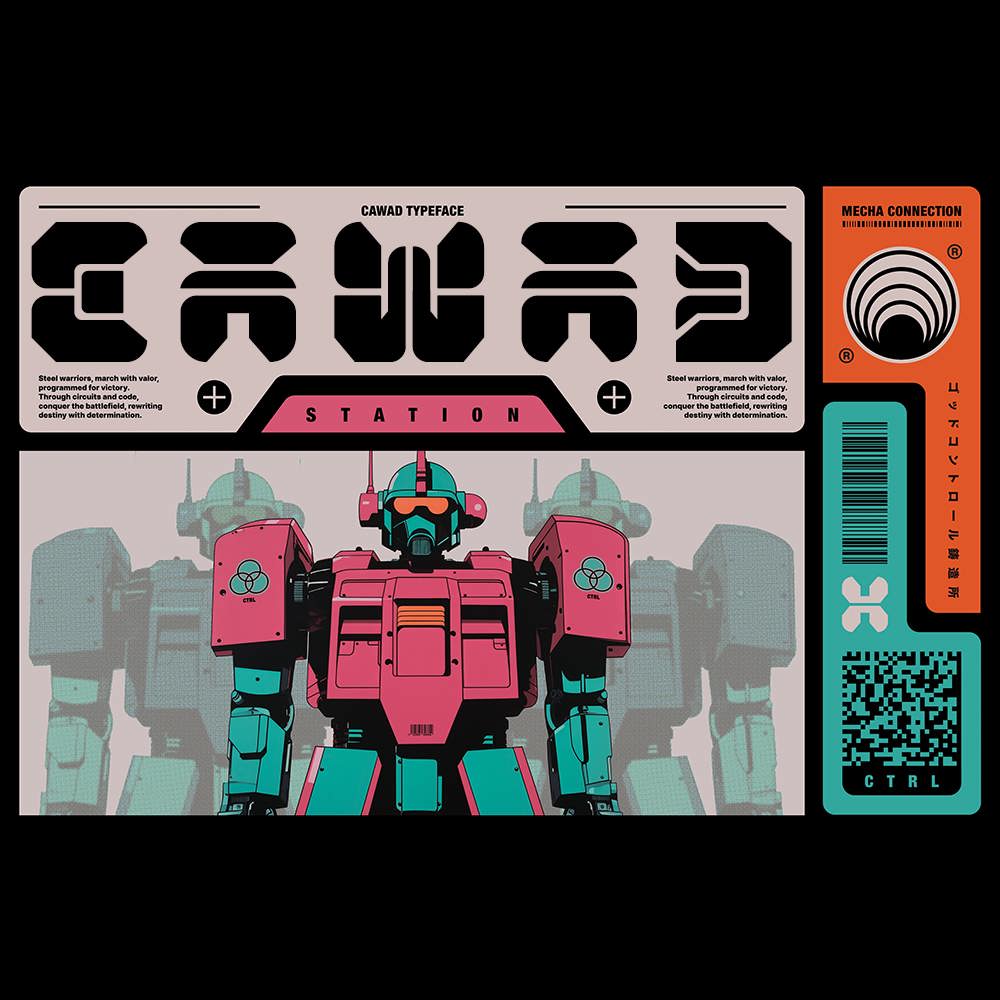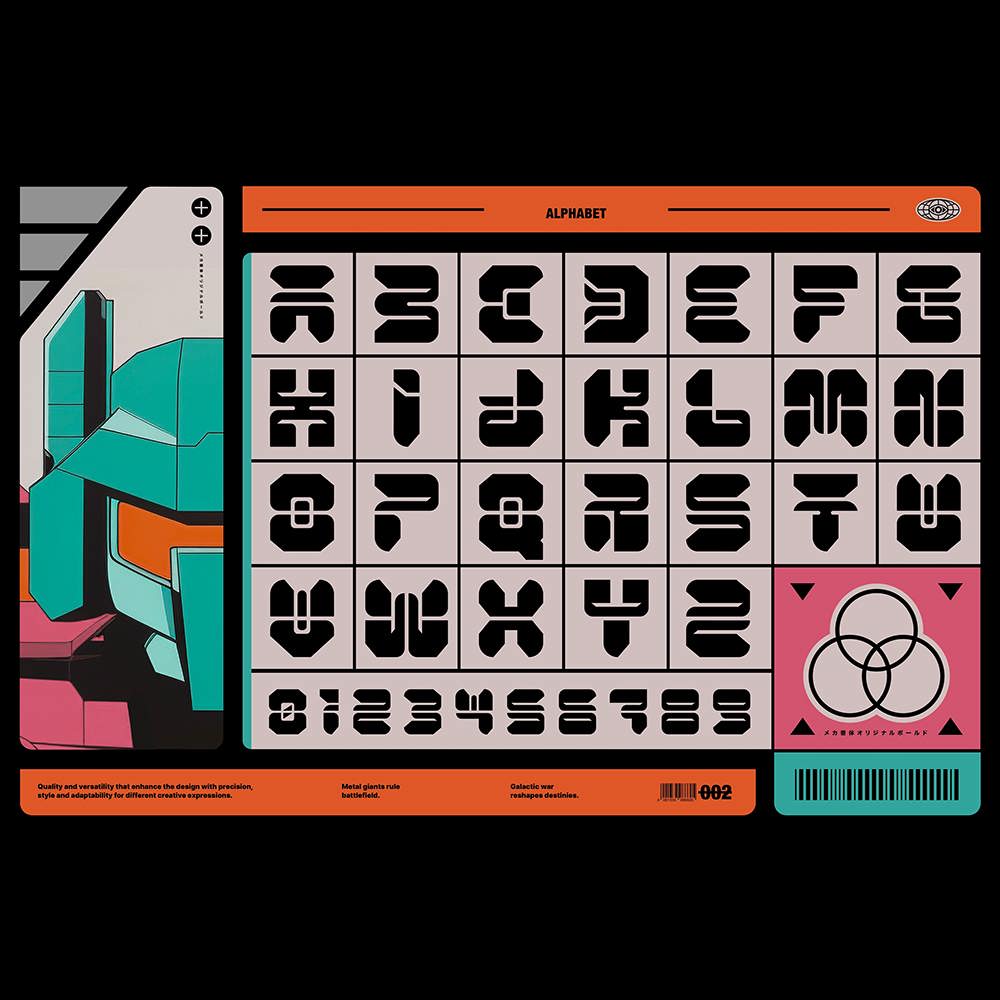
دانلود فونت انگلیسی Cawad Font
فونت پرمیوم و انگلیسی Cawad Font یک فونت نمایشی با سبک دهه ۹۰ میلادی است. هر کاراکتر یک شاهکار از آیندهنگری که برای جلب توجه و معروف کردن طرحهاتون عالی می باشد! این فونت برای هر چیزی که مربوط به غذا، کودکان، تصاویر کودکان، عناوین کتاب، عنوان وبسایت، نوشتن ویدیو یا هر چیزی که ممکن است بخواهید برای کسب تجربه در نیازهای طراحی گرافیک امتحان کنید، عالی است.
مزایای استفاده از فونت لاتین Cawad چیست؟